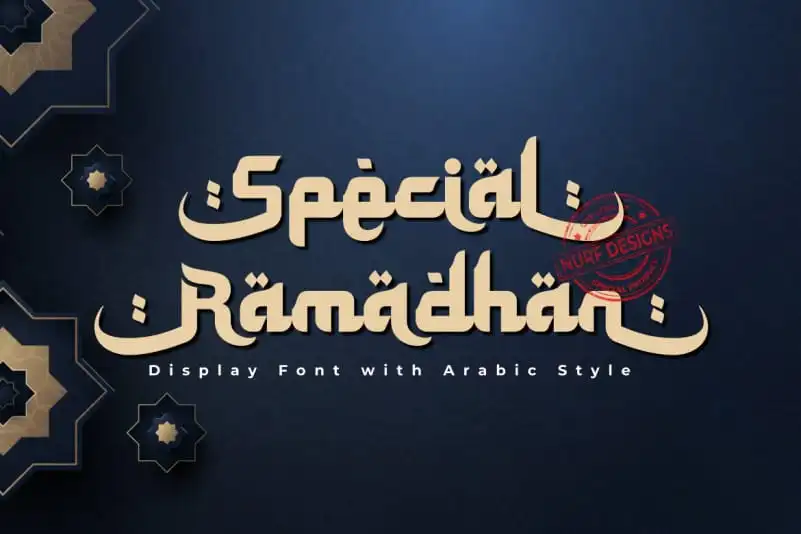
Special Ramadhan Display Font – Download Grátis
A Special Ramadhan Display Font é uma elegante escolha para quem busca estilos arábicos modernos. Seja para rótulos de produtos orientais ou design editorial, essa fonte traz a essência dos países árabes diretamente para seu trabalho. Ideal para qualquer projeto que busque um clima do Oriente Médio com elegância e sofisticação, ela reforça o desejo de expressar uma cultura única através do texto. Combinada com outras fontes e cores, essa fonte proporciona um enquadramento perfeito para representar um design arábico contemporâneo. Sem dúvidas, é a escolha certa para designers que buscam transmitir os sentimentos da Ramadã ou qualquer outra celebração islâmica de maneira impressionante.